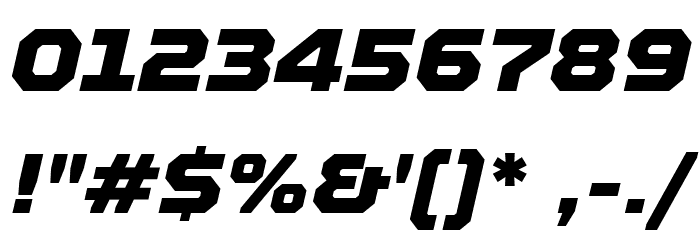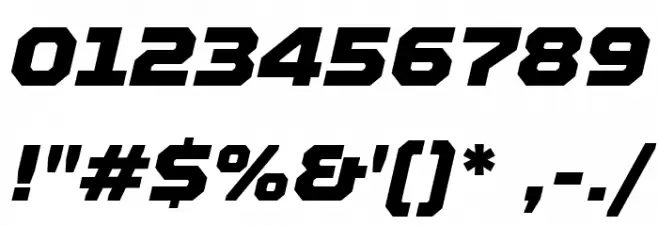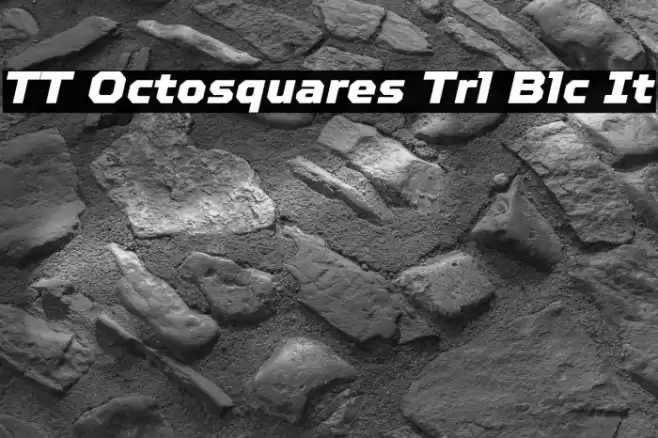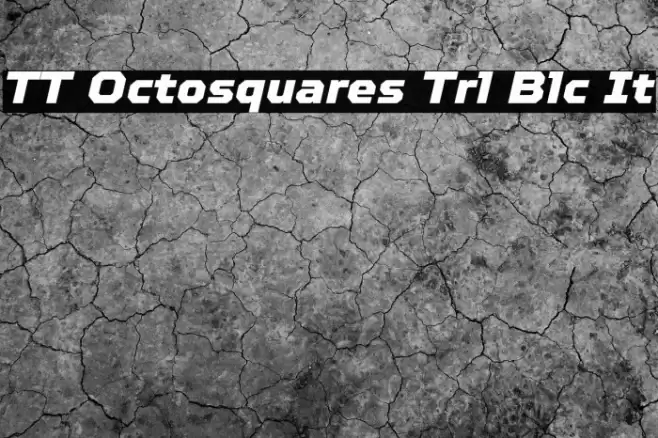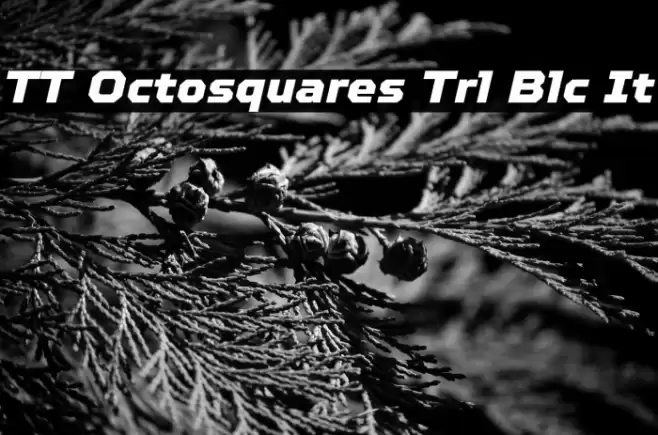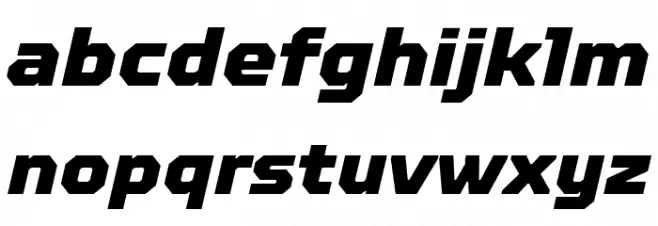
TT Octosquares Trl Blc It Font
| الفئات | Thick |
| مائل | Yes |
| حالة الاستخدام | Logos, Headlines, Posters |
| مشاريع مقترحة | Ideal for futuristic branding, tech-related projects, sports team logos, and dynamic poster designs. |